글로벌 폰트 및 서체 기술 선도 기업 모노타입(Monotype)이 11월 13일부터 15일까지 부산 벡스코에서 열린 ‘지스타(G-STAR) 2025’ B2B 전시에 참가했다. 모노타입은 현장에서 게임 경험 전반에 걸쳐 타이포그래피가 수행하는 핵심 역할을 조명했으며, 개발·디자인·퍼블리싱 팀을 위한 폰트 활용 사례와 효율적인 워크플로를 소개했다. 모노타입은 유명 글로벌 게임 스튜디오와 협력해 다양한 타이틀에 게임 폰트를 제공해 왔으며, 다국어 현지화와 라이선스 운영을 포함한 통합 솔루션을 지원한 경험이 있다.
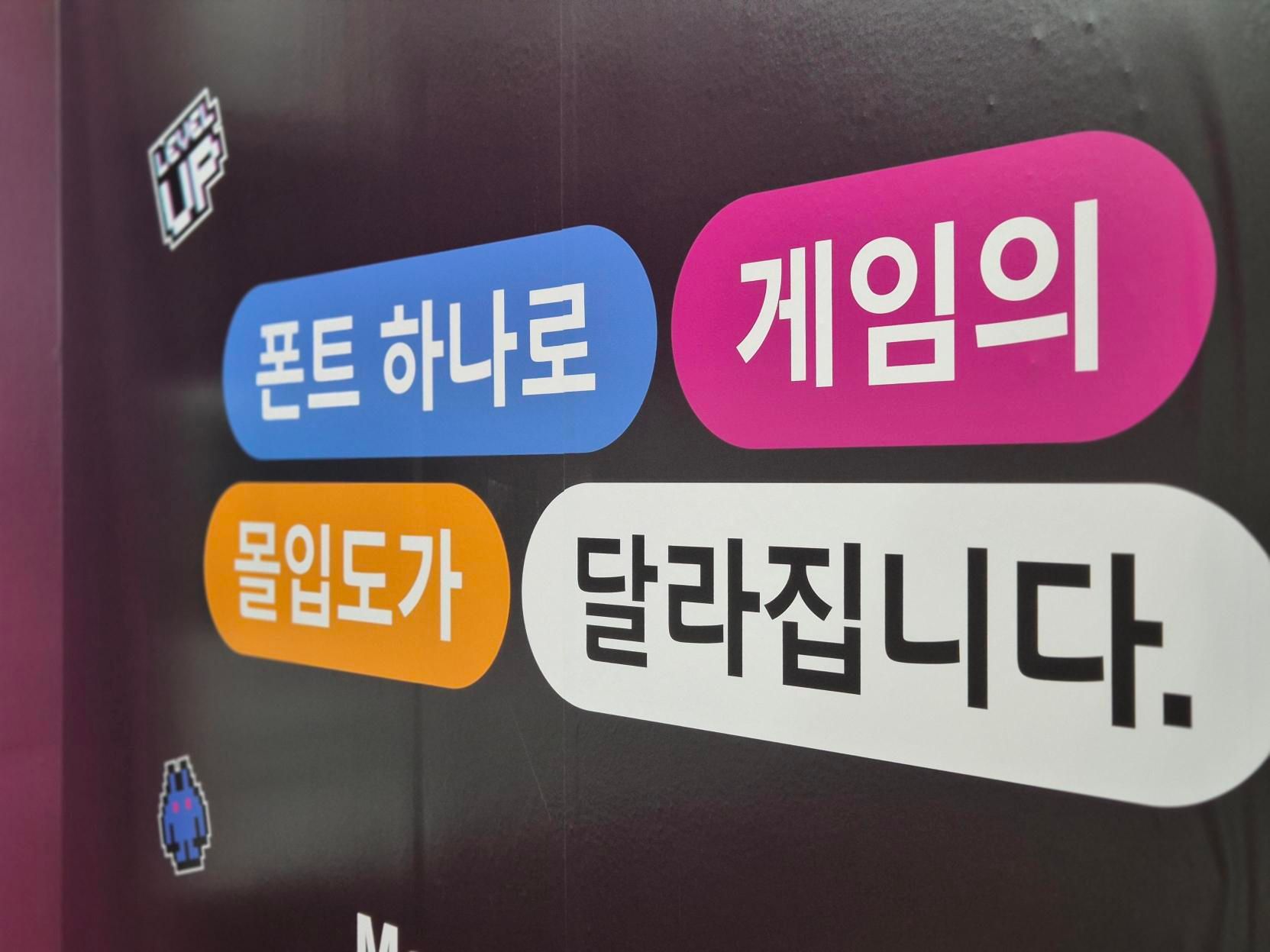
게임에서 폰트는 단순한 글자가 아니다. 세계관의 분위기를 만들고, 캐릭터의 개성을 드러내며, 플레이 흐름을 읽기 쉽고 누구나 접근 가능하게 하는 핵심 요소다. UI와 자막, 내러티브, 인게임 상점, 마케팅 콘텐츠까지 폰트가 하나의 톤앤매너를 유지해 브랜드 경험을 통일한다. 또한 다국어 지원, 라이선스 준수, 성능 최적화 등에서도 명확한 기준과 선택이 필요하다. 모노타입은 이를 해결하기 위한 사례와 실무 솔루션을 지스타 현장에서 소개했다.
이번 전시에서 모노타입은 다음과 같은 주제를 중심으로 상담 및 시연을 진행했다. 첫째, 캐주얼부터 AAA까지 장르 전반에 적용 가능한 가독성 중심의 UI 타이포그래피 설계다. 화면 해상도와 표시 밀도, 동적 움직임과 애니메이션, 야간·저조도 환경 등 실제 플레이 상황을 고려한 글꼴 선택과 계층 설계를 제안했다.
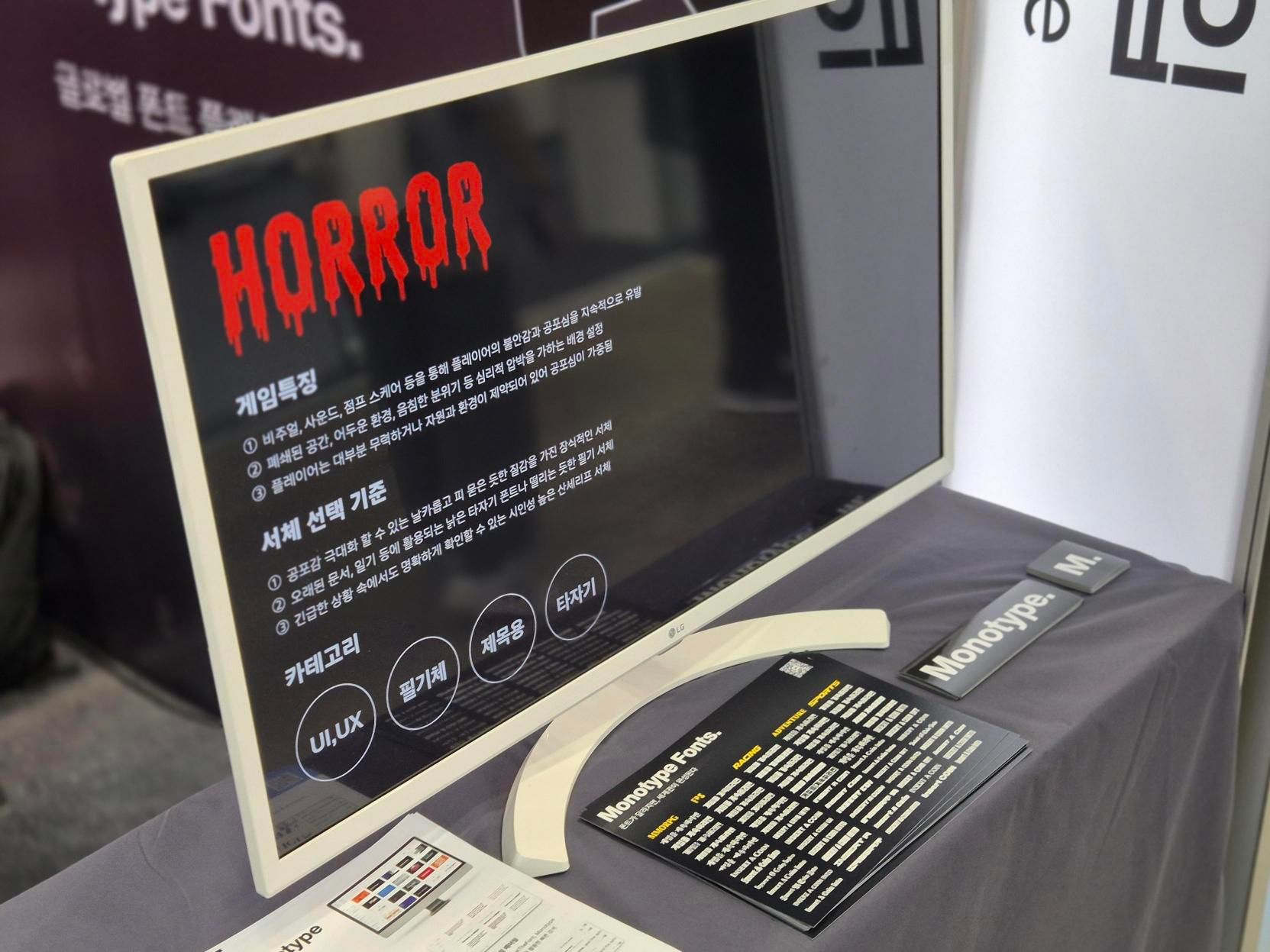
둘째, 글로벌 출시를 전제로 한 다국어 현지화 전략이다. 한글과 라틴, 일본어·중국어 등 주요 스크립트 간의 스타일 일관성과 폭·행간·문장부호 처리, 숫자·아이콘 조합 지침을 통해 UI 붕괴를 방지하는 방법을 공유했다.
넷째, 접근성과 성능이다. 가독성 표준 준수, 색 대비 및 난독증 친화 설정, 변수 폰트(variable font)를 활용한 자원 효율화 등 플레이어 경험을 개선하는 실무 팁을 제공했다.
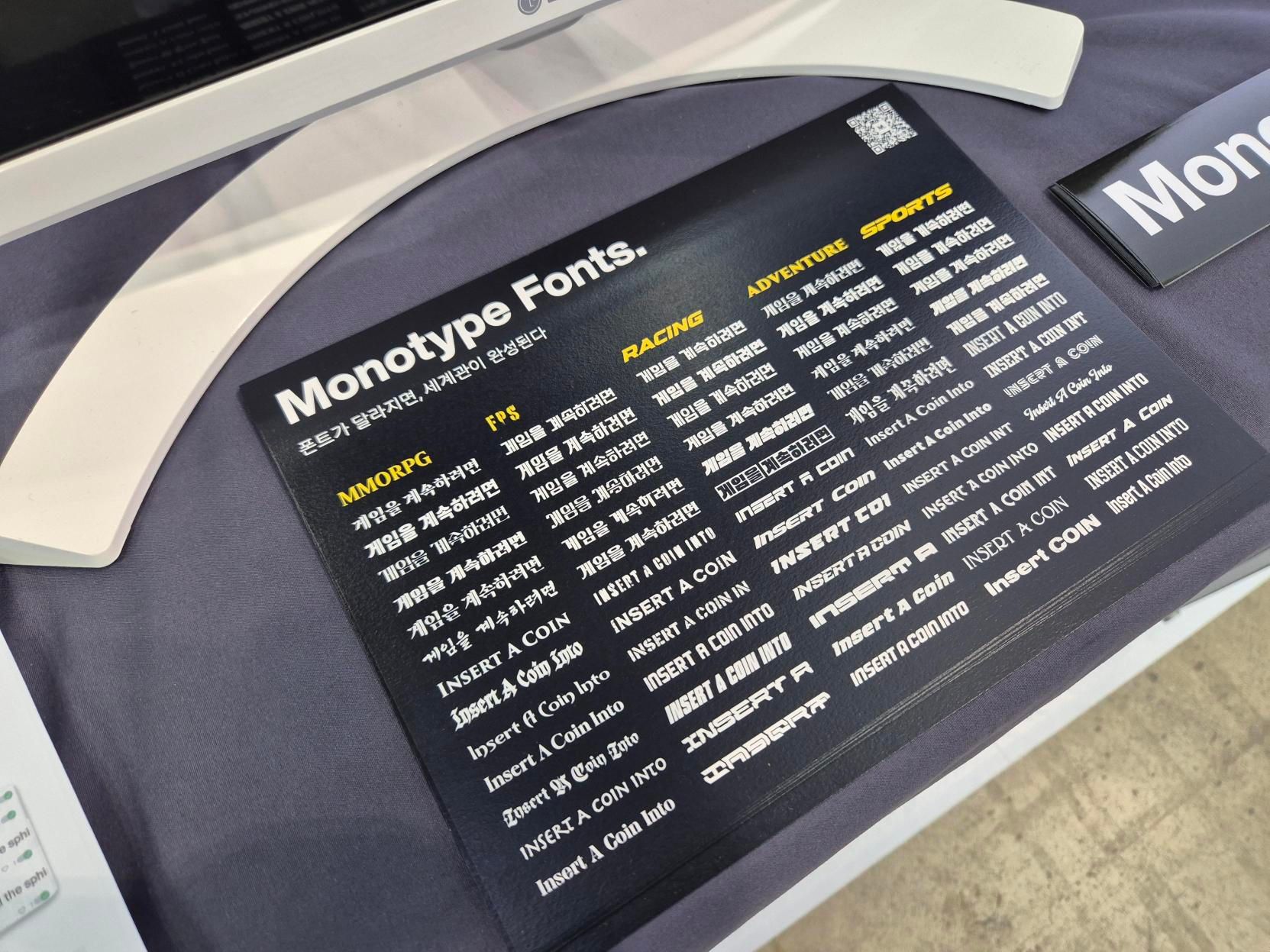
모노타입 코리아는 게임은 텍스트가 화면에 머무는 순간을 넘어 글자가 세계를 구축하는 매체로, 일관된 타이포그래피 전략은 플레이 흐름을 매끄럽게 하고, 감정선을 강화하며, 글로벌 플레이어에게 동일한 품질의 경험을 제공한다며, 지스타 현장에서 한국의 개발사와 스튜디오가 한 단계 앞선 폰트 전략으로 글로벌 경쟁력을 확보할 수 있도록 돕겠다고 밝혔다.